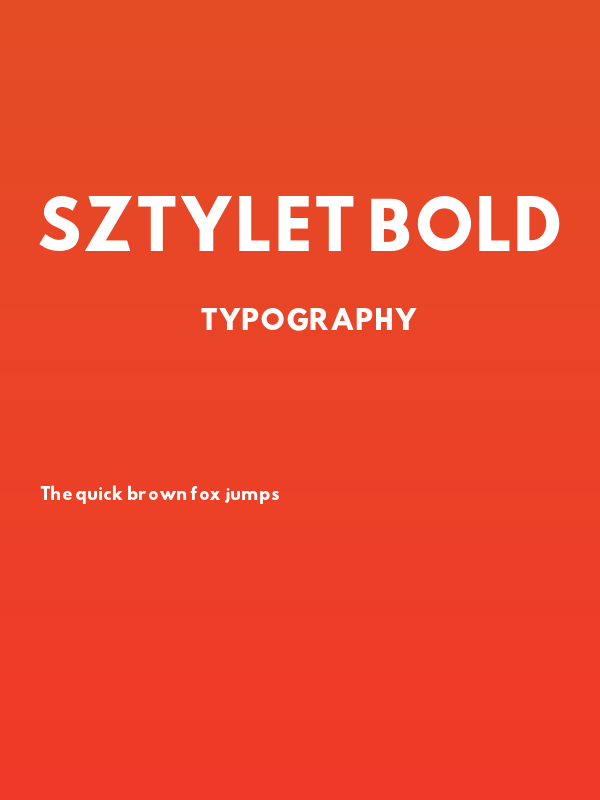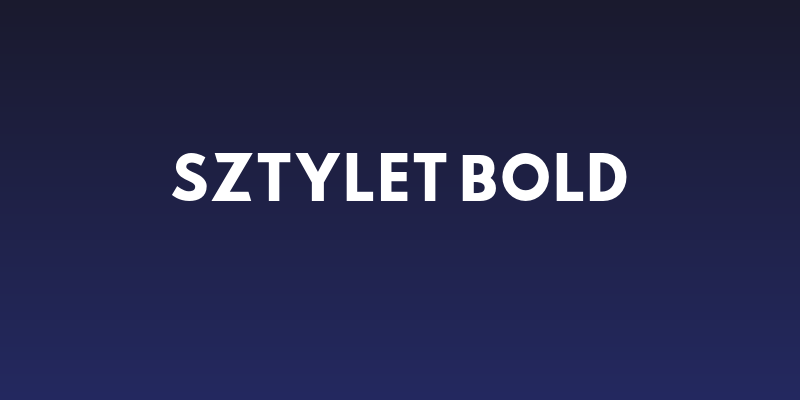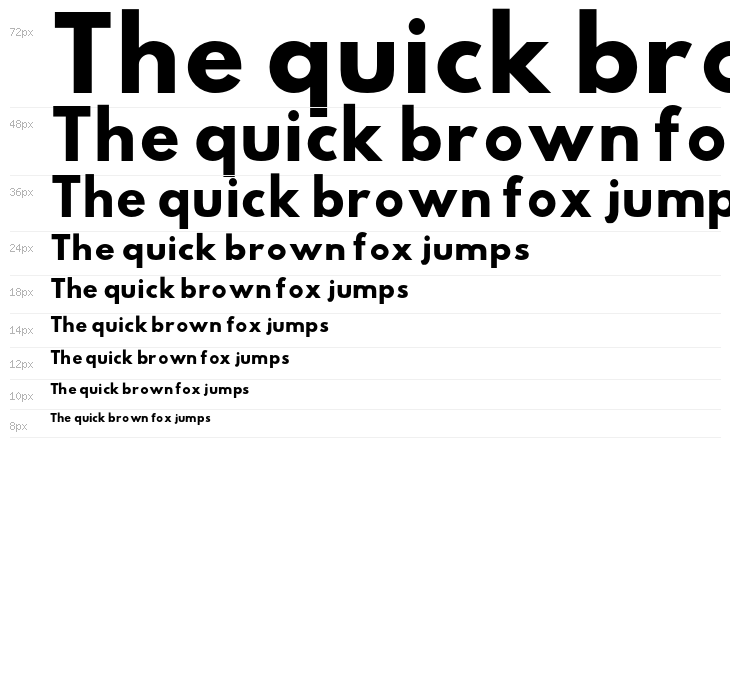
Sztylet Bold Font
| Caz de utilizare | Headlines, Logos, Branding |
| Proiecte propuse | Ideal for branding, advertising, headlines, and digital media where a bold statement is needed. |